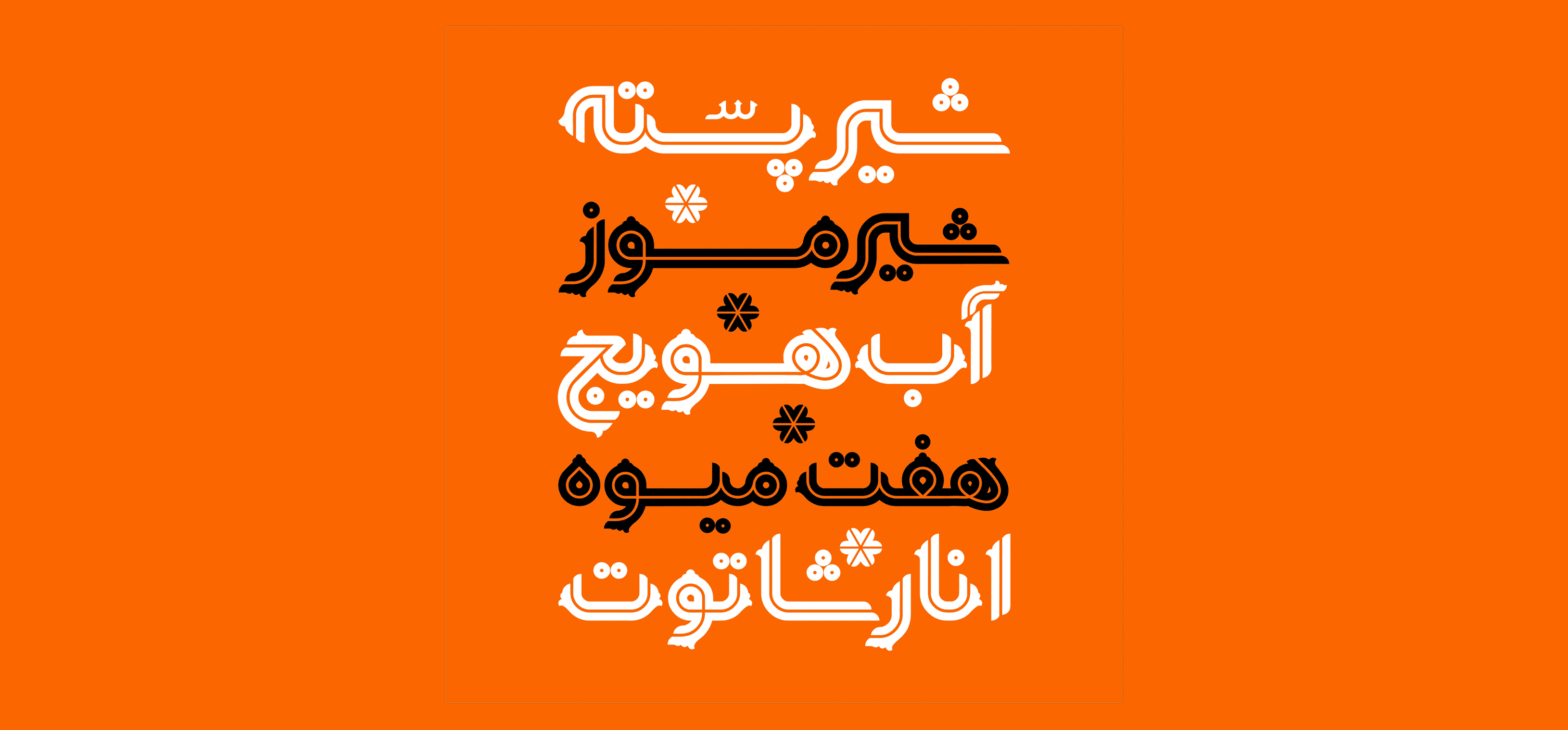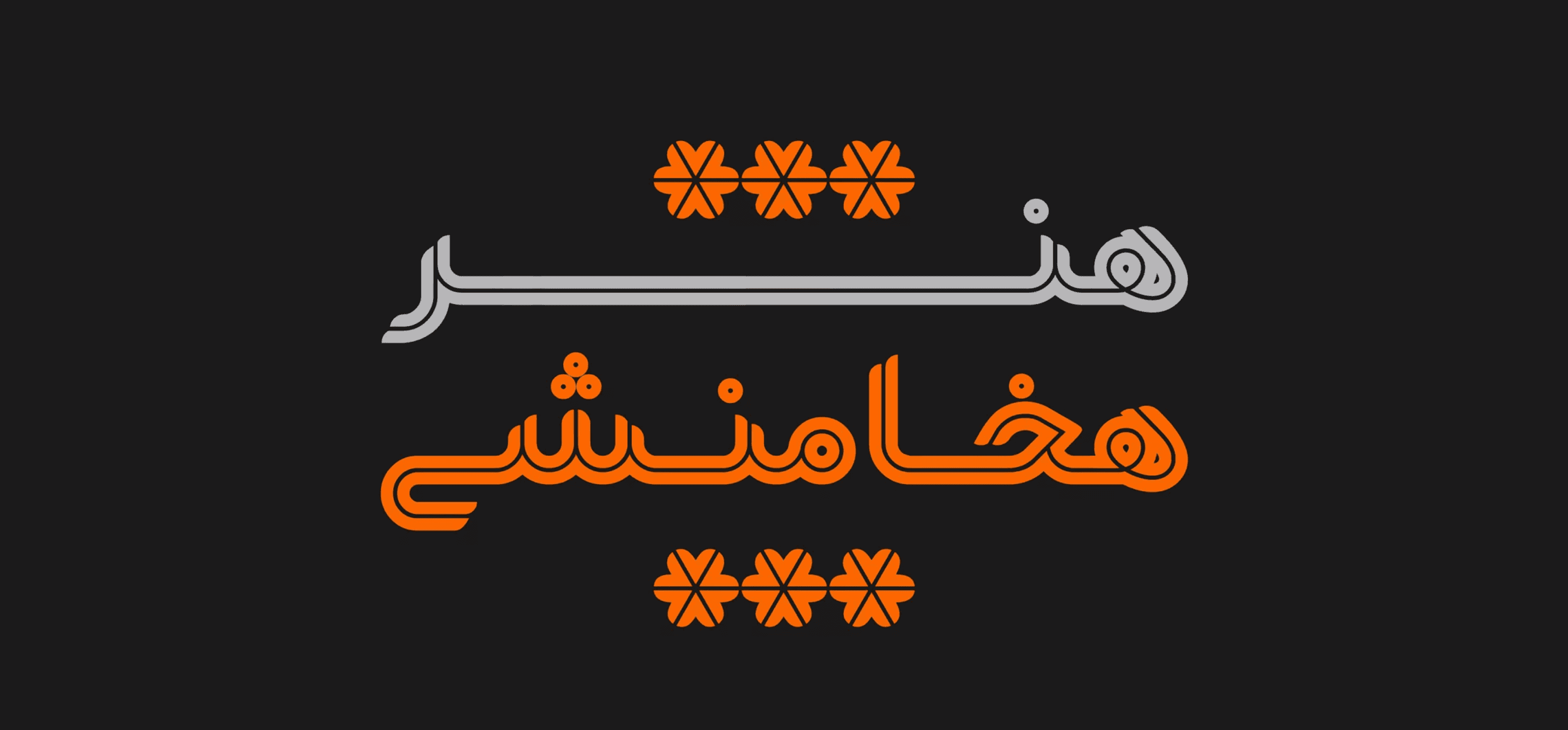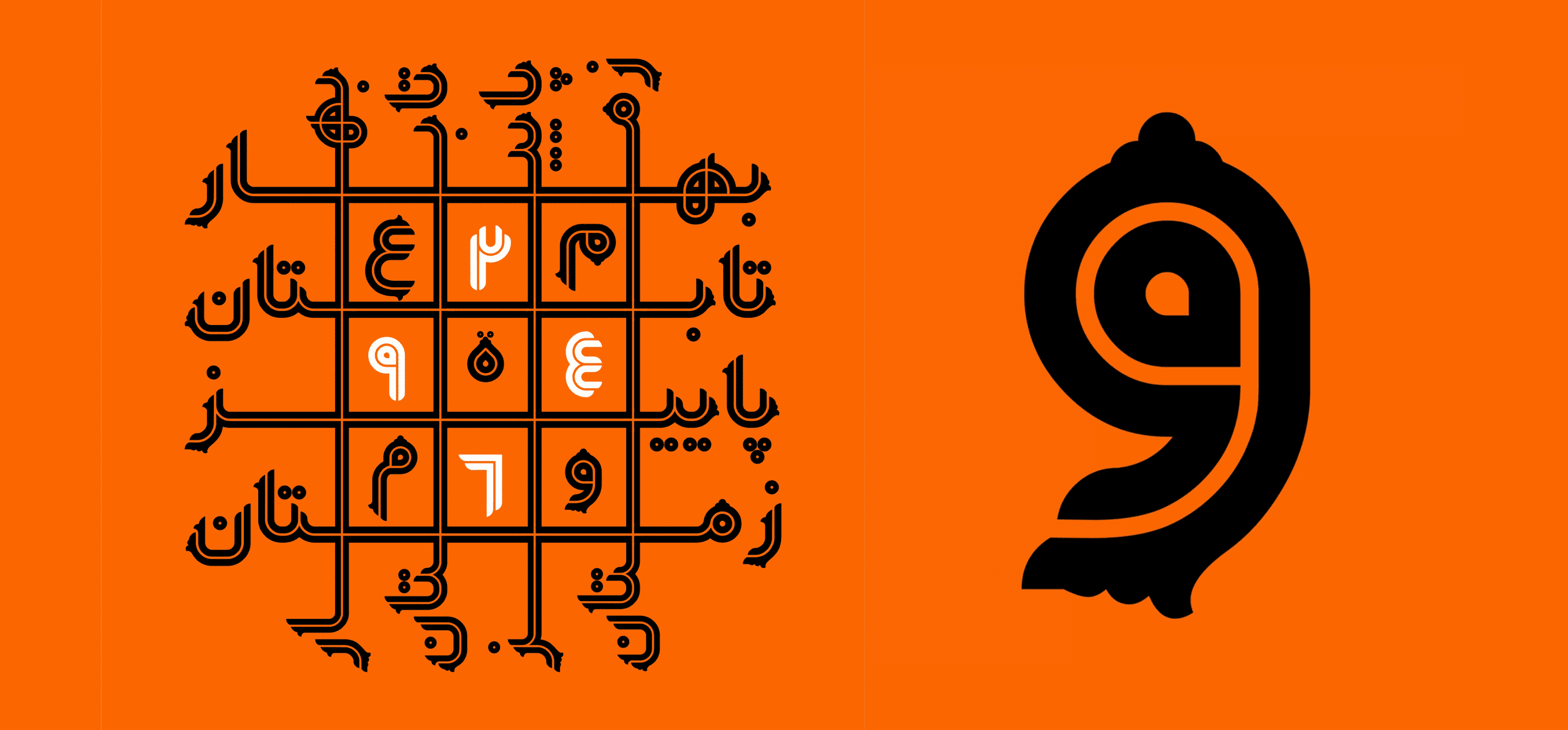
"يكتا" هو خط ذو طابع هندسي يتّسم بأسلوب داخل-الخط (in-line) وزخارف تزيينية مميزة.
تزداد القوة البصرية والتأثيرية لخط يكتا بفضل هذه الزخارف، التي تستحضر الزخارف الإسلامية التقليدية (نقوش أسليمي)، مما يمنحه رغم طابعه الهندسي، طابعًا إيرانيًا أصيلًا ويجعله مناسبًا للموضوعات الثقافية.
عادةً ما يتجنّب المصممون استخدام الخطوط الهندسية (مثل "يكان") في التصميمات ذات الطابع الديني أو الأدبي، لكن خط "يكتا" – على الرغم من بنيته الهندسية – يُعدّ خيارًا مناسبًا للإعلانات ذات الطابع الديني، الأدبي، أو الفني.